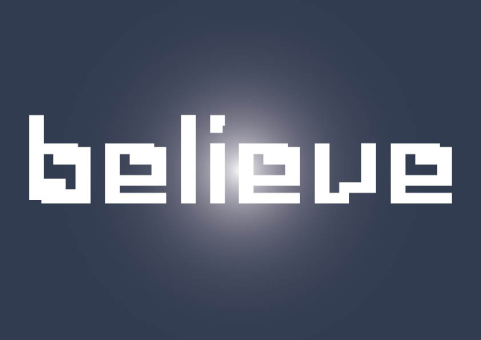
believe
"believe", è un progetto nato grazie all'evento artistico CAMERABOOK, creato da Massimo Arduini nella manifestazione ACCADEMIA IN CAMPO 2013, presso gli spazi del Campo Boario dell'Accademia di Belle Arti di Roma.
Il concept principale della rassegna, consiste nella reinterpretazione in forma artistica di un libro fuori catalogo della casa editrice Essegi di Ravenna.
Nel progetto "believe", il libro reinterpretato è una biografia di un prete ravennate, poi diventato Monsignore, don Bendazzi. Il libro si intitolava originariamente "Sulle rime del don - Vita e inediti di don Anacleto Bendazzi".
Il don Bendazzi, fine enigmista, appassionato di anagrammi, dotto latinista e molto altro, amava giocare di continuo con le parole, inserendo spesso queste dinamiche anche nell'insegnamento con i suoi studenti. Queste solo alcune delle sue "particolarità" di prete davvero fuori dal comune.
In tutto questo, ho progettato un nuovo carattere, pensato direttamente dal layout del libro e dal suo modulo. Questo carattere, incarna il sentimento scherzoso, particolare, seppur intimo del prete di provincia. E lo stesso carattere, realmente digitalizzato, maiuscole/minuscole e glifi più comuni, entra nel libro originale, contaminandolo. In secondo luogo, l'installazione che scaturisce da queste dinamiche, è la creazione della parola "believe", nome dell'opera e del nuovo carattere, creata con la moltiplicazione modulare delle pagine stesse del libro originale. Scala 1:4 per motivi di spazio. E visibile presso la manifestazione CAMERABOOK.
Circa 550 tagli formato A4 divisi ulteriormente in 8 moduli: il lettering è composto da circa 4.400 pagine/moduli. La riproduzione totale del libro per circa 40 volte, copertina e quarta comprese.
Quello che rimarrà dell'esperienza totale, oltre all'esposizione e all'esperienza progettuale ovviamente, sarà una nuova font gratuita e disponibile al download, nella versione 1.0, oltre che l'installazione o quel che ne rimarrà, visto che il clima dei giorni d'ottobre, stanno "consumando" l'opera per la sua inevitabile fragilità di partenza. Mentre il libro verrà acquisito in archivio come da progetto CAMERABOOK, dalla casa editrice Essegi di Ravenna.
Il concept principale della rassegna, consiste nella reinterpretazione in forma artistica di un libro fuori catalogo della casa editrice Essegi di Ravenna.
Nel progetto "believe", il libro reinterpretato è una biografia di un prete ravennate, poi diventato Monsignore, don Bendazzi. Il libro si intitolava originariamente "Sulle rime del don - Vita e inediti di don Anacleto Bendazzi".
Il don Bendazzi, fine enigmista, appassionato di anagrammi, dotto latinista e molto altro, amava giocare di continuo con le parole, inserendo spesso queste dinamiche anche nell'insegnamento con i suoi studenti. Queste solo alcune delle sue "particolarità" di prete davvero fuori dal comune.
In tutto questo, ho progettato un nuovo carattere, pensato direttamente dal layout del libro e dal suo modulo. Questo carattere, incarna il sentimento scherzoso, particolare, seppur intimo del prete di provincia. E lo stesso carattere, realmente digitalizzato, maiuscole/minuscole e glifi più comuni, entra nel libro originale, contaminandolo. In secondo luogo, l'installazione che scaturisce da queste dinamiche, è la creazione della parola "believe", nome dell'opera e del nuovo carattere, creata con la moltiplicazione modulare delle pagine stesse del libro originale. Scala 1:4 per motivi di spazio. E visibile presso la manifestazione CAMERABOOK.
Circa 550 tagli formato A4 divisi ulteriormente in 8 moduli: il lettering è composto da circa 4.400 pagine/moduli. La riproduzione totale del libro per circa 40 volte, copertina e quarta comprese.
Quello che rimarrà dell'esperienza totale, oltre all'esposizione e all'esperienza progettuale ovviamente, sarà una nuova font gratuita e disponibile al download, nella versione 1.0, oltre che l'installazione o quel che ne rimarrà, visto che il clima dei giorni d'ottobre, stanno "consumando" l'opera per la sua inevitabile fragilità di partenza. Mentre il libro verrà acquisito in archivio come da progetto CAMERABOOK, dalla casa editrice Essegi di Ravenna.